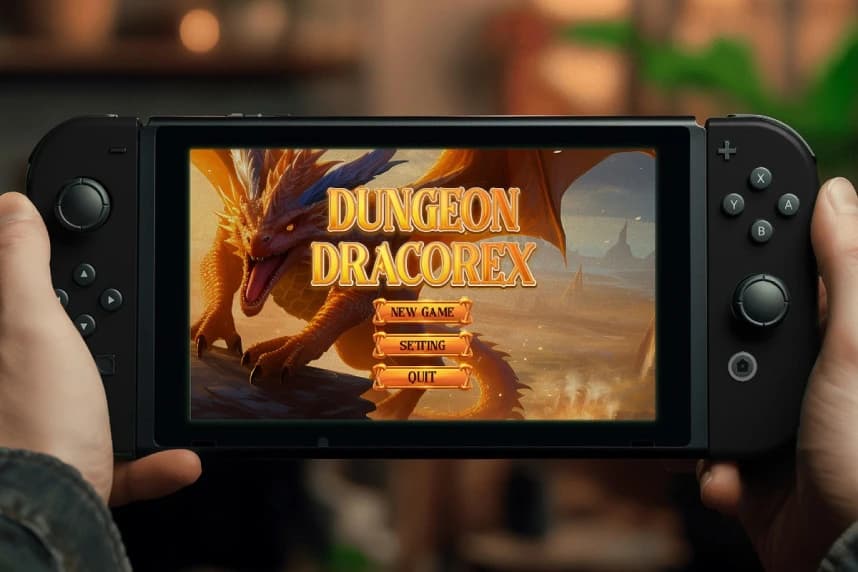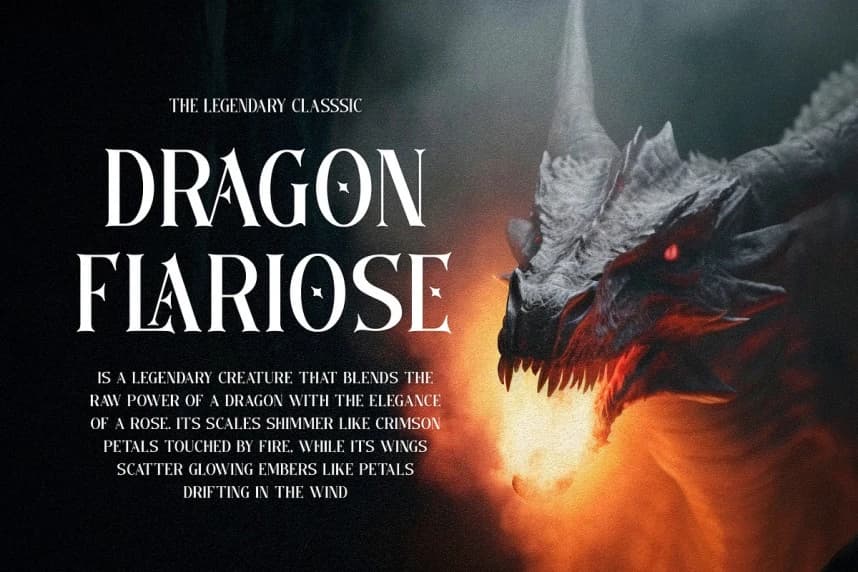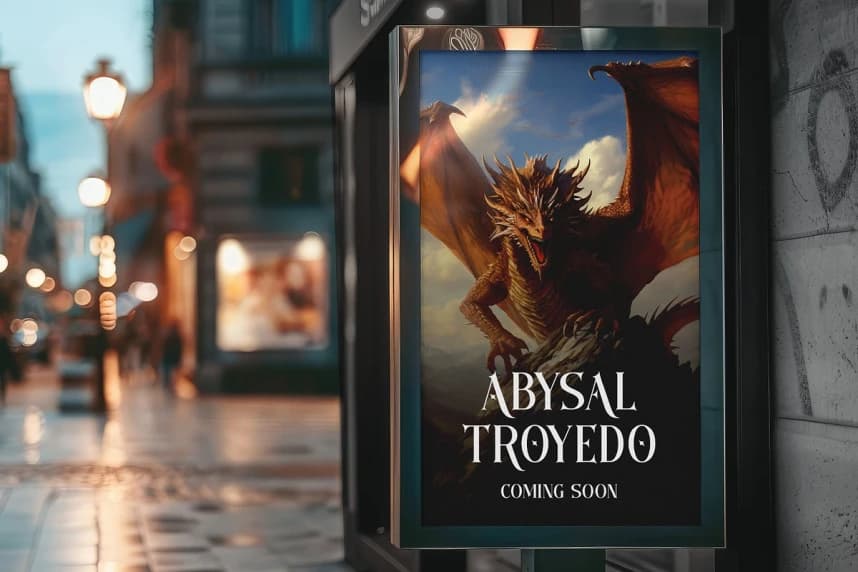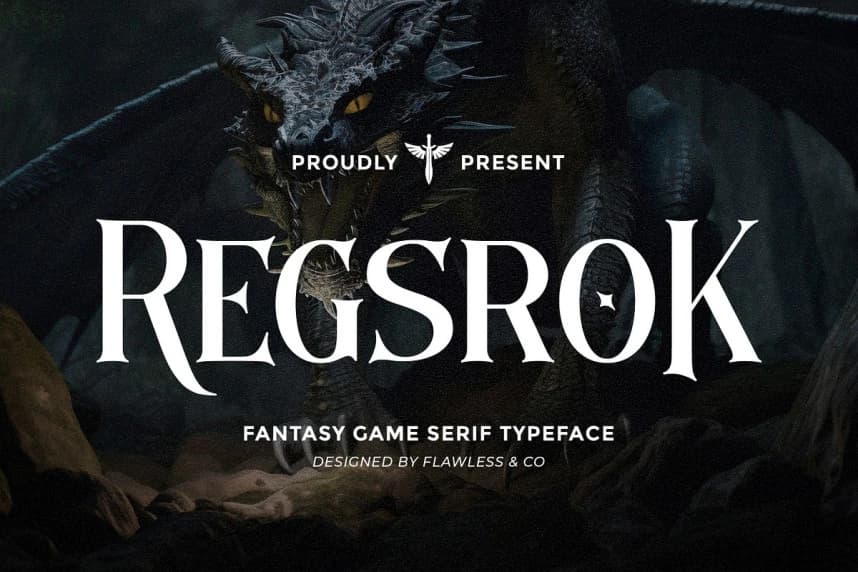
Regsrok Font, büyülü dünyaların özünü ve destansı anlatımı yakalamaya devam ederken daha hafif, daha zarif bir dokunuşla tasarlanmış rafine bir fantezi oyun serifi yazı tipidir. Keskin, savaş izleri taşıyan ayrıntıları ve kahraman harf biçimleriyle.
Regsrok Font, büyülü dünyaların özünü hâlâ yakalarken daha hafif, daha zarif bir dokunuşla tasarlanmış rafine bir fantastik oyun serif tipidir. Keskin, savaş yıpranmış ayrıntıları ve kahraman harf biçimleriyle